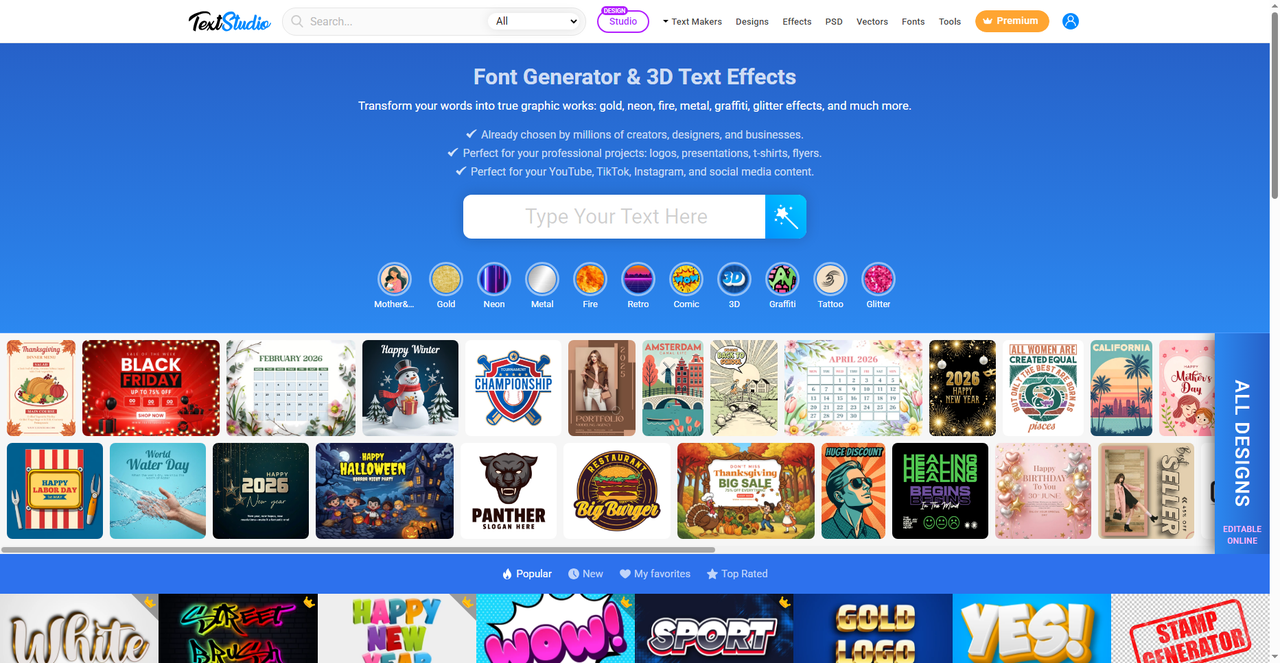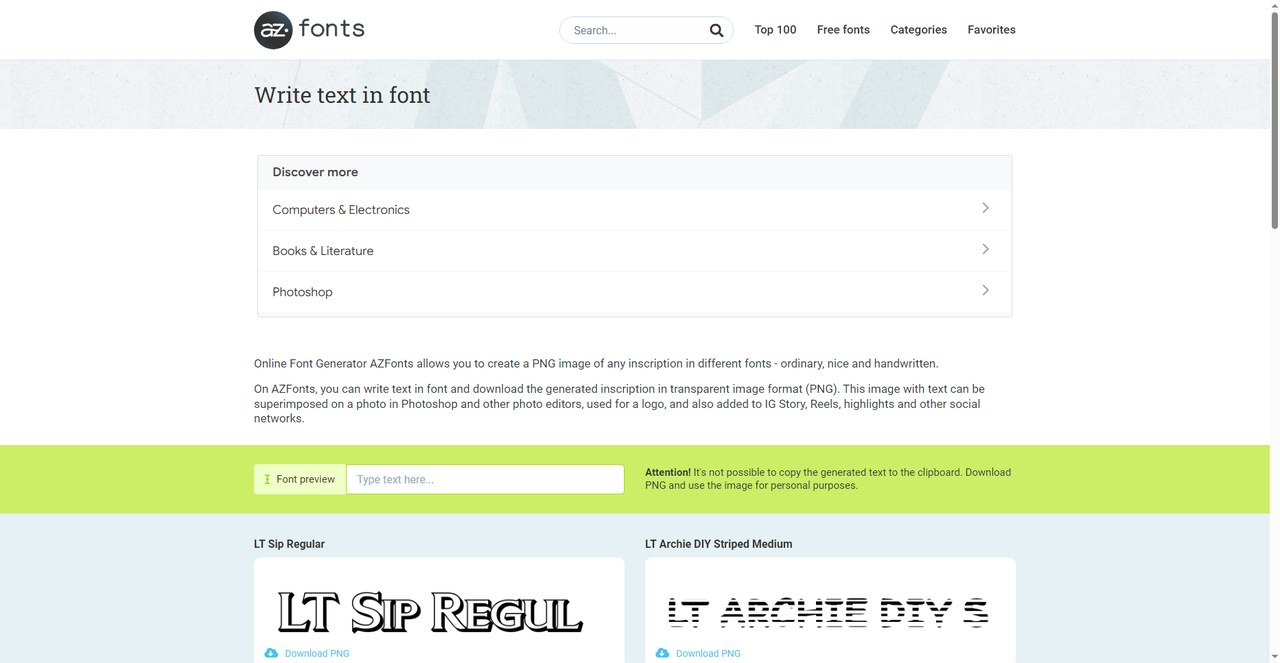
不会做艺术字?这几个生成器打开网页就能用
做PPT封面或者海报标题时,文字往往是第一眼被看到的内容,这篇文章整理的几个生成器,有的专攻3D立体效果,有的擅长金属质感,有的支持动态GIF,还有的可以基于正规字体库生成带授权信息的图片,基本能满足从自媒体配图到商业海报的各种文字特效需求。
字由和其他网页生成器不太一样,它不只是输出一张特效图,而是把字体管理和特效生成放在同一个工作流里。客户端里的字体库按风格分好类,手写体、书法体、卡通体、黑体、宋体各自有独立入口,目前收录的字体数量不少,做海报前先在库里浏览,找到气质匹配的字体激活试用,整个过程不用切换软件,省去了在字体网站下载安装、再打开PS调效果的繁琐步骤。字体激活后在设计软件里直接就能调用,不需要走系统安装流程。
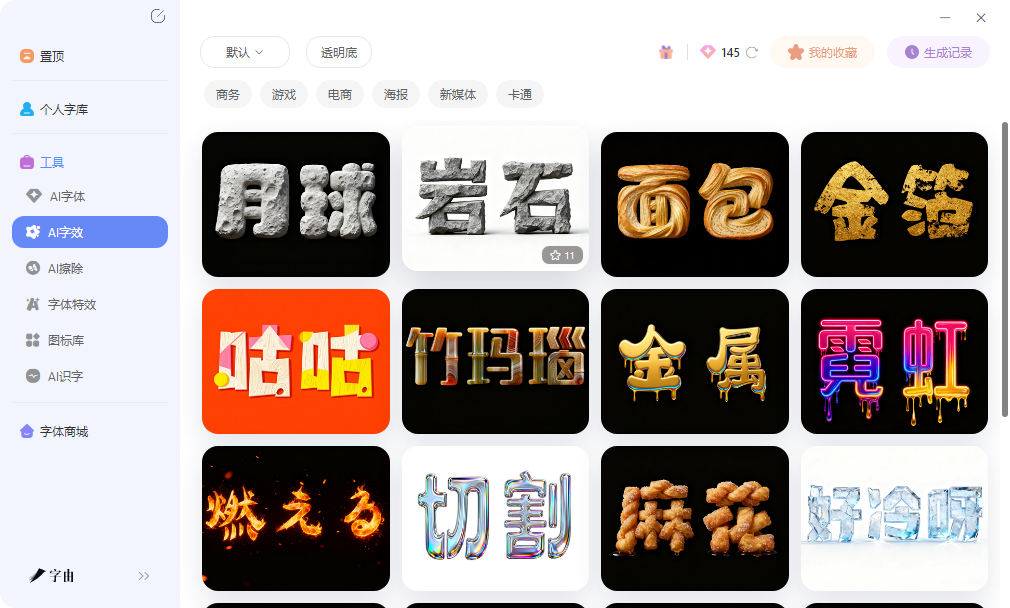
字由的AI字效支持在网页版直接操作,输入文案后选择霓虹、金属、浮雕、投影等效果类型,每种效果下还有细分变体,比如金属类就分拉丝、镜面、生锈等不同质感。调好色温、强度、光影角度后,生成的是带透明背景的PNG图片,可以直接拖进PS、AI、PPT或者剪贴到文档里。这个功能对临时需要做几张图但电脑里没有装设计软件的人很友好,打开浏览器就能出图,不需要学习复杂的图层操作。登录后会有一定免费额度,预览阶段不消耗,确认效果后再正式输出,对偶尔做几张图的用户比较友好。
2、Text Studio
Text Studio是一个专门做文字特效的在线工具,模板库偏向3D立体、金属切割、霓虹发光、火焰燃烧、冰晶雕刻、木纹石纹等冲击力强的风格。选择模板后输入文字,可以调整主色、辅色、光影角度、表面材质、文字间距、背景透明度等参数,生成高分辨率的PNG或GIF。网站支持中文输入,部分模板对中文字符的渲染效果不错,笔画细节和间距处理比较到位,做中文海报时不会出现笔画粘连或者间距失衡的情况。
3、AZFonts Font Generator
AZFonts的生成器基于其庞大的字体库,可以把文字转换成网站上收录的任意字体样式。输入文案后,系统会列出所有匹配的字体,每种字体都附带预览图和授权信息,商用还是个人使用一目了然。这个工具的优势在于字体来源正规,做商业项目时不用担心侵权风险,生成结果可以下载PNG图片,也可以直接复制文字样式到设计稿里。
对于需要批量查看不同字体效果、快速对比选字的场景,AZFonts的效率很高。输入一段品牌标语,系统同时展示几十种字体的渲染效果,横向对比比逐个打开字体文件快得多。
4、Text to Image Generator
这个工具走图片生成路线,输入文字后选择字体、颜色、背景、阴影、描边等参数,生成的是PNG图片。支持上传自定义字体文件,如果你手里有一款特别的字体想做成标题图,可以直接上传使用,不需要先把字体装到系统里。输出尺寸可以调节,从几百像素到几千像素都能设置,背景也可以设置成透明或者纯色,适合做公众号封面、PPT标题、电商主图或者打印物料。
界面比较简洁,没有复杂的模板库,但自由度更高,对知道自己想要什么效果的人来说更顺手。文字颜色、背景颜色、阴影方向、描边粗细都可以手动调节,调好后实时预览,确认无误再下载。
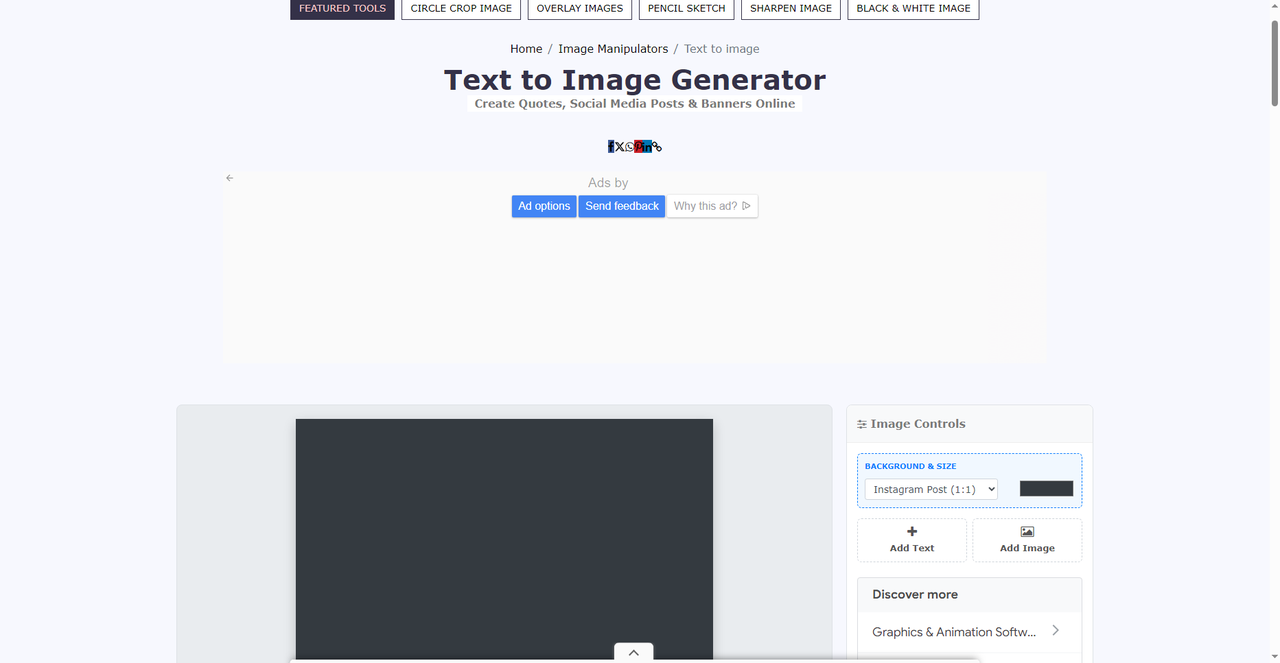
5、Font Generator
这个网站可以把普通文字转换成各种Unicode花式字体,适合社交媒体文案美化。输入文字后,系统提供几十种花体、粗体、斜体、空心字、双线字、气泡字样式,一键复制就能粘贴到微博、小红书、抖音简介、朋友圈文案或者Telegram频道里。这种转换走的是Unicode字符替换路线,不是生成图片,所以在任何支持Unicode的平台上都能正常显示,手机、电脑、不同APP之间复制粘贴不会出现乱码,显示一致性很好,发朋友圈或者写小红书笔记时不用担心别人手机上看到的是乱码方块。
网站还整合了颜文字和特殊符号库,可以配合花式字体一起使用,让文案排版更有层次感。比如发一条产品推广文案,标题用粗体花字,正文用普通字体,中间插入几个特殊符号做分隔,整体阅读体验比纯文字好很多。对于日常发动态、写社群公告、做邮件标题、写直播预告来说,这种轻便的转换方式比打开PS做图省事得多,几秒钟就能让普通文案变得更有辨识度。缺点是样式相对简单,没有立体或光影特效,不适合做海报标题,更适合纯文字场景的装饰和排版美化。
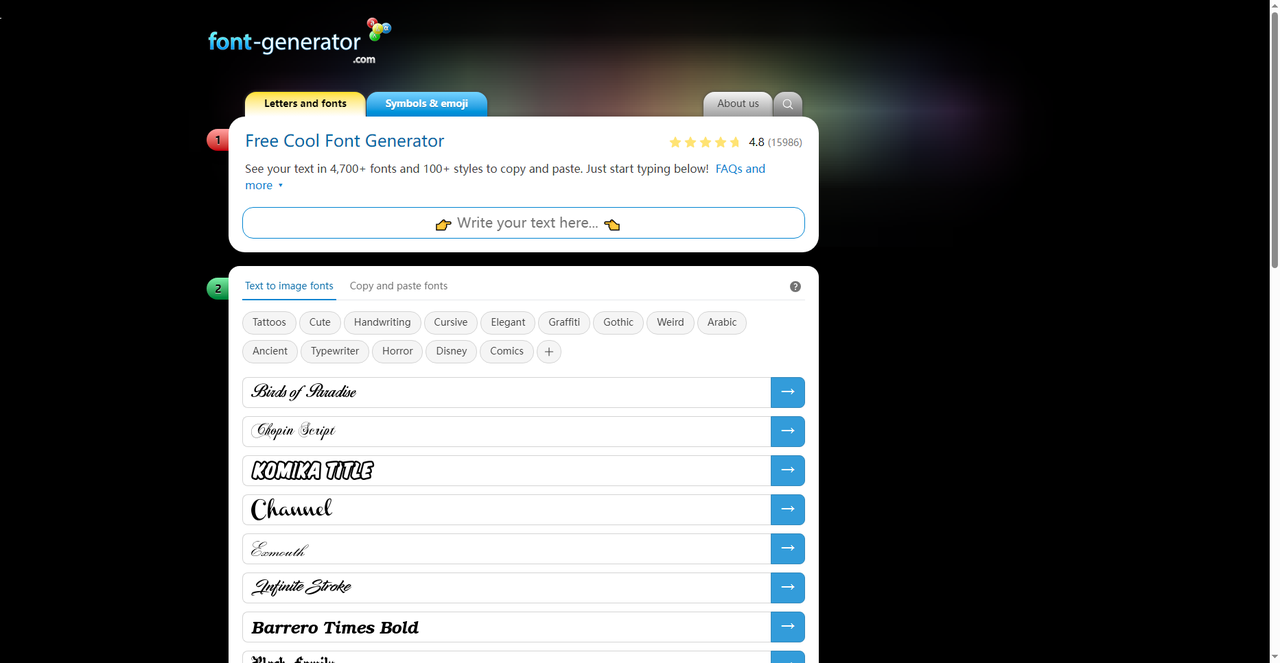
这几个工具打开网页就能用,门槛都不高。Font Generator适合日常社交文案快速换风格,Text to Image Generator对想自定义参数的人更友好,AZFonts在字体授权方面比较规范,Text Studio的特效精细度更高。字由把字体管理和特效生成连在一起,从选字体到出图不用切换软件。按自己的使用频率和项目类型来选,偶尔做几张图用网页工具足够,长期做设计可以搭配字由的字体库一起用,工作流更顺畅,出图效率明显提升。关键是这些工具都不需要安装,打开浏览器就能开始,试错成本很低。